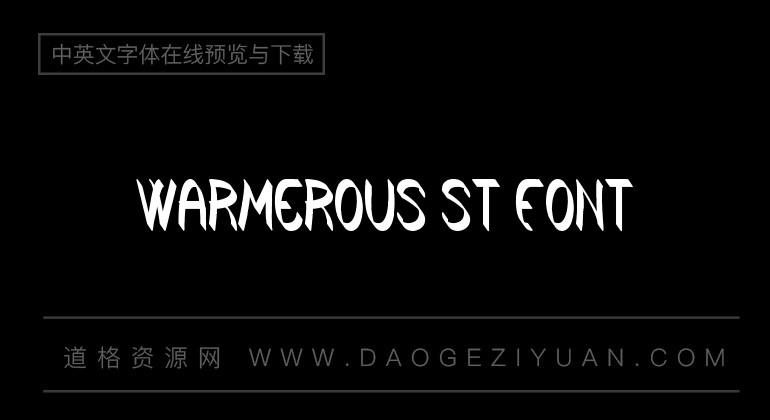
Warmerous St Font 是一款优美、时尚的手写字体,它的设计灵感来自于手写字母和书写风格。 Warmerous St Font 的特点是具有自然、流畅的线条和独特的笔画感觉,使得它在海报、宣传册、包装设计和其他设计项目中表现出色。 Warmerous St Font 提供了多种不同的字形和符号,包括大写字母、小写字母、数字、标点符号和其他符号。该字体的使用非常灵活,可以适用于各种设计风格和项目类型,从精致的手绘风格到现代简约风格,都可以完美表现。 此外,Warmerous St Font 还提供了多种字重和字体样式,比如粗体、斜体等,以满足不同的设计需求。如果您正在寻找一款高质量、多功能的手写字体,那么 Warmerous St Font 绝对值得一试!内容介绍
Warmerous St Font是一款非常不错的手写艺术字体,具有很好的视觉感,适合于文化类的宣传设计、商业类品牌的广告和产品包装设计以及个性化文字排版等较多场景。